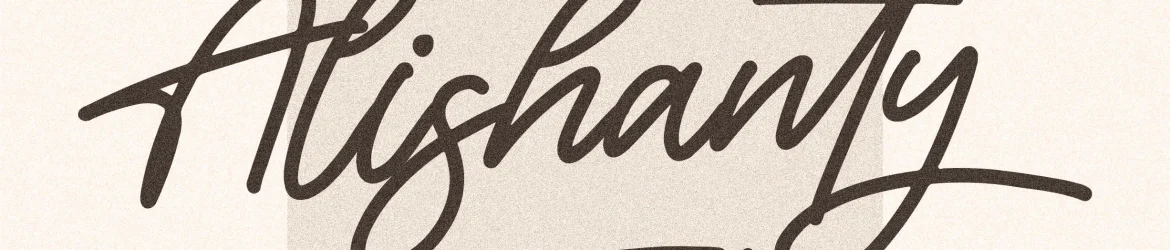
Alishanty Font – Fonte Grátis
Alishanty Font
A Alishanty Font é uma elegante escolha para aqueles que buscam um toque autêntico em suas criações digitais ou físicas. Especificamente projetada como uma fonte escrita a mão, ela se destaca perfeitamente em uma variedade de projetos, desde as identidades visuais e os logos até designs de móveis, embalagens de produtos, e até mesmo em objetos pessoais como tênis de sapatos. Suas linhas delicadas e seu caráter natural tornam-a perfeita para adicionar um toque único em mugs personalizados, estampas de camisetas ou capas de livro, deixando o seu trabalho ainda mais especial. Ideal tanto para projetos que valorizam a elegância minimalista quanto para aqueles que buscam um design mais rústico e pessoal, Alishanty é uma excelente opção para criações do cotidiano, desde cartões de convite até marcadores de livros. Seja para um evento especial ou para adicionar um toque único em sua próxima campanha publicitária, esta fonte escrita a mão traz um sabor autêntico que não pode ser substituído por qualquer outra.